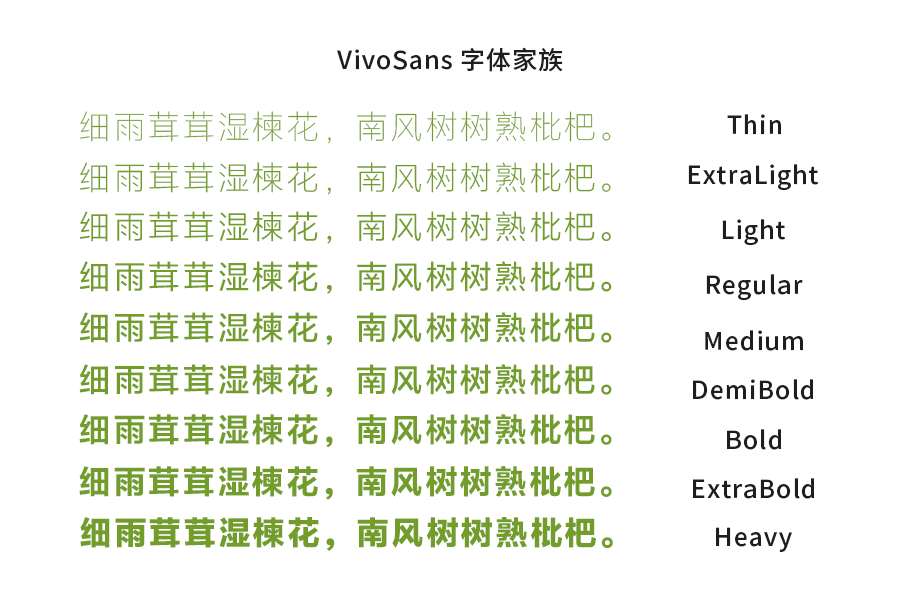
在追求高效与美感并存的现代设计中,字体的选择往往能直接影响作品的最终呈现效果。以下四款免费商用字体,凭借其卓越的设计品质与多场景适用性,成为设计师工具库中的“万能钥匙”。
1.思源宋体 CN
作为思源黑体的宋体兄弟,这款由Adobe Type发布的泛CJK字体家族,以7种粗细和65,540个字形构建了庞大的视觉系统。其字形设计既保留传统宋体的典雅骨架,又融入现代排版逻辑,支持拉丁、希腊、西里尔等多语言字符,实现跨文化设计的无缝衔接。无论是严肃出版物还是国际品牌物料,思源宋体都能传递兼具文化深度与专业气质的视觉语言。
2. 思源黑体 SC
由Adobe与Google联合打造的思源黑体,自2014年发布便成为开源字体的标杆。这款字体通过严谨的字间距优化与灰度控制,在屏幕与印刷介质间达到罕见的视觉一致性。其简洁中性的气质,既适合科技产品的界面文字,也能驾驭商业海报的醒目标题,是追求现代感与实用性的设计师首选。
3. 阿里巴巴普惠体 3
阿里巴巴推出的第三代普惠体,将品牌基因转化为设计语言。瘦长字形与提高的重心赋予其轻盈活力的气质,笔画简化策略(如标题字省略出脚)更强化了信息传达效率。特别适合互联网产品或年轻化品牌的视觉系统,既能体现专业可信度,又能传递创新品牌的温度感。
4. vivo Sans
vivo Sans的设计哲学可概括为“少即是多”。通过去除装饰性细节、强化笔画对比度,这款字体在保障易读性的同时,创造出呼吸感十足的排版空间。其理性克制的美学,尤其适合需要长时间阅读的场景,如电子书界面、企业宣传册等,让读者能专注内容本身而非被字体分散注意力。
这四款字体不仅覆盖了从传统出版到数字界面的全场景需求,更通过免费商用的开放政策,降低了创作门槛。它们不仅是设计工具箱中的“基础款”,更是经得起时间考验的经典选择。尝试将它们融入你的作品,或许会发现:优秀的字体,本身就是一种无声的设计智慧。